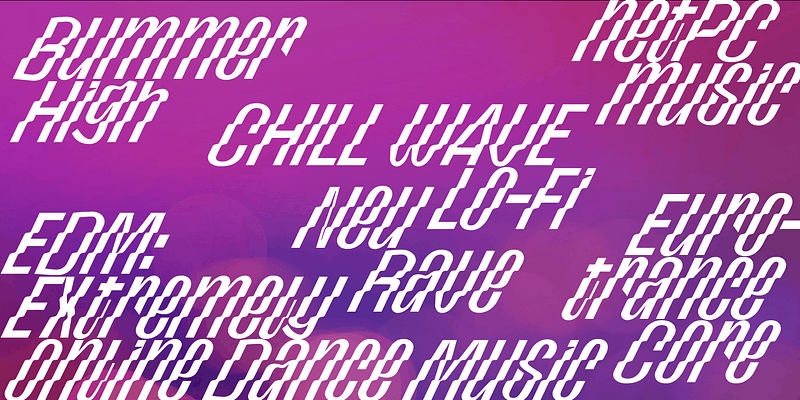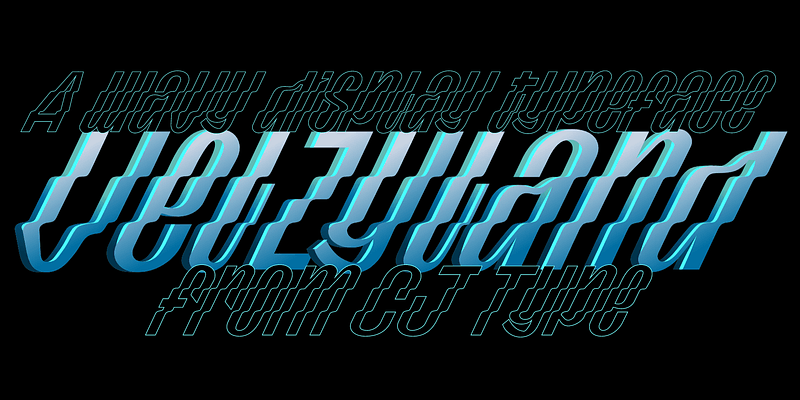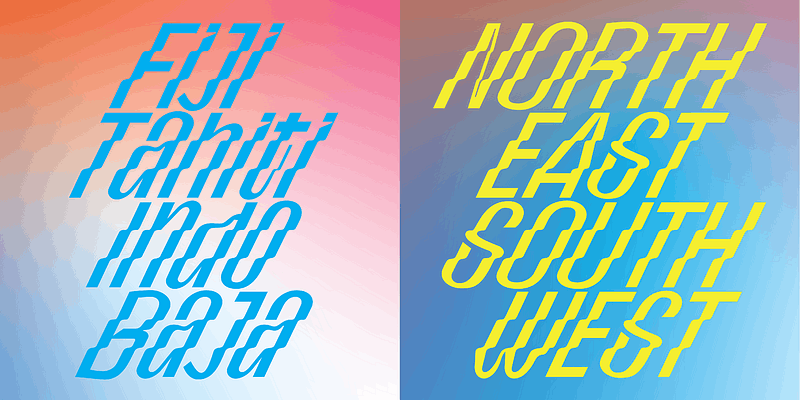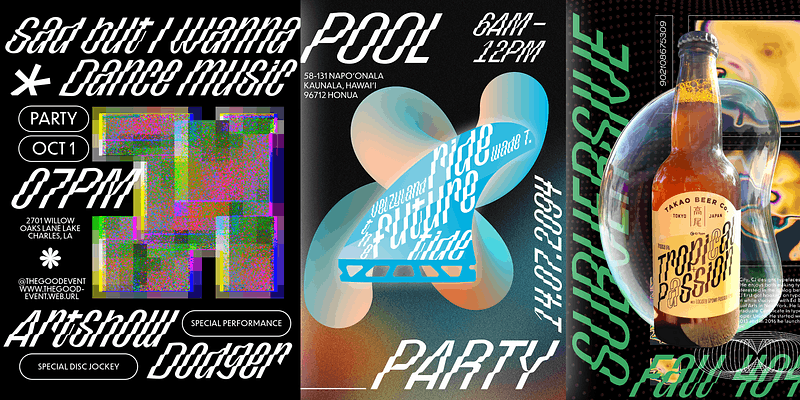
Die ausdrucksstarke, wellenförmige Akzidenzschrift Velzyland von CJ Dunn basiert auf einem Schriftzug, den der Schrift-Designer für das Surf-Lifestyle-Bekleidungsunternehmen Vast entworfen hat. Der Name „Velzyland“ geht auf einen Surfspot an der Nordküste der hawaiianischen Insel Oahu zurück, nahe dem Geburtsort von CJ Dunn. Die Formen der Buchstaben neigen sich in einem steilen Winkel nach unten und erinnern an die Wellen an diesem Ort. Anders als bei den traditionellen Schriften, die mit dem Surfen in Verbindung gebracht werden, sind in dieser Schrift die Wellen in die Struktur der Buchstabenformen integriert. Obwohl die Schrift an die Natur und den Ozean erinnert, ist sie vom digitalen Design inspiriert und kontrastiert sanfte Kurven mit scharfen Strichen, um eine moderne Anmutung zu erzielen.
Die Buchstabenformen von Velzyland eignen sich für das Branding eines Yogastudios oder einer Privatbrauerei ebenso wie für die Identität eines Festivals für elektronische Musik oder einer Ausstellung zeitgenössischer Kunst. Die Schrift verfügt über einen umfangreichen Interpunktions- und Akzentzeichensatz, der die meisten ost- und westeuropäischen Sprachen unterstützt. „Velzyland“ wurde als „Unicase“-Schrift konzipiert, bei der Groß- und Kleinbuchstaben die gleiche Höhe haben. Sie unterscheiden sich zwar in der Form, aber viele von ihnen können gegeneinander ausgetauscht werden (als „Alternative“). Dies ist besonders praktisch für Logos oder einfach, um die Textur der Typografie zu variieren. Aufgrund des extremen Neigungswinkels der Velzyland empfiehlt sich die Verwendung einer diagonalen Grundlinie. Der enge Zeilenabstand kann auch gut mit dem kompakten horizontalen Buchstabenabstand harmonieren. Die markanten, fett gedruckten Buchstaben eignen sich hervorragend für große Titel auf Fotos, faszinierende Social-Media-Posts oder kraftvolle Überschriften im Web- oder Printdesign.